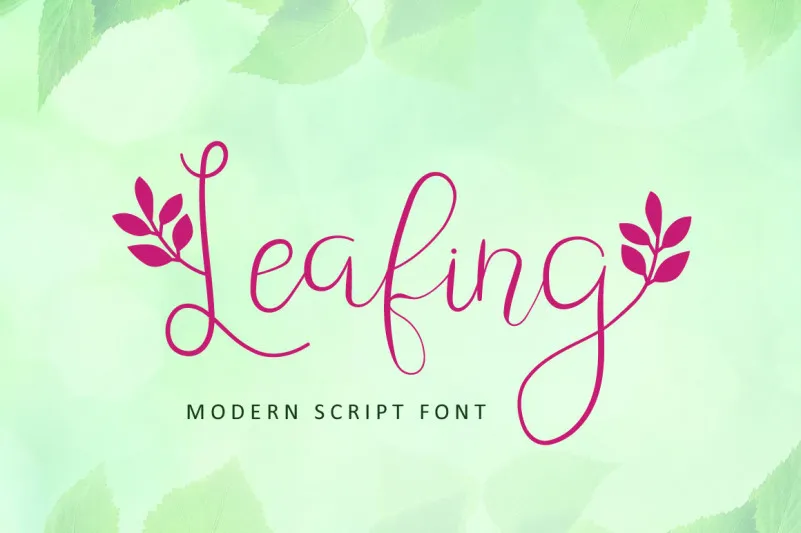
Leafing – Modern Script Font – Download Grátis
Leafing é uma fonte moderna com leves toques florais que transmite um sentimento natural. Ela combina elementos tipográficos de escrita a mão com detalhes vegetais para criar um estilo único e autêntico. Esta elegante fonte de letra feita à mão é perfeita para aplicações diversas, como headlines, logotipos, convites de casamento, aniversários de Valentine, marca, embalagens, publicidade, marca d’água, entre outras. Ela vem em maiúsculas, minúsculas, pontuação, símbolos e números, e oferece suporte a recursos privados da área (PUA) do OpenType. Se você precisa de uma fonte que combine elegância com naturalidade para seus projetos gráficos, Leafing é uma ótima opção.
Designer: illushvara